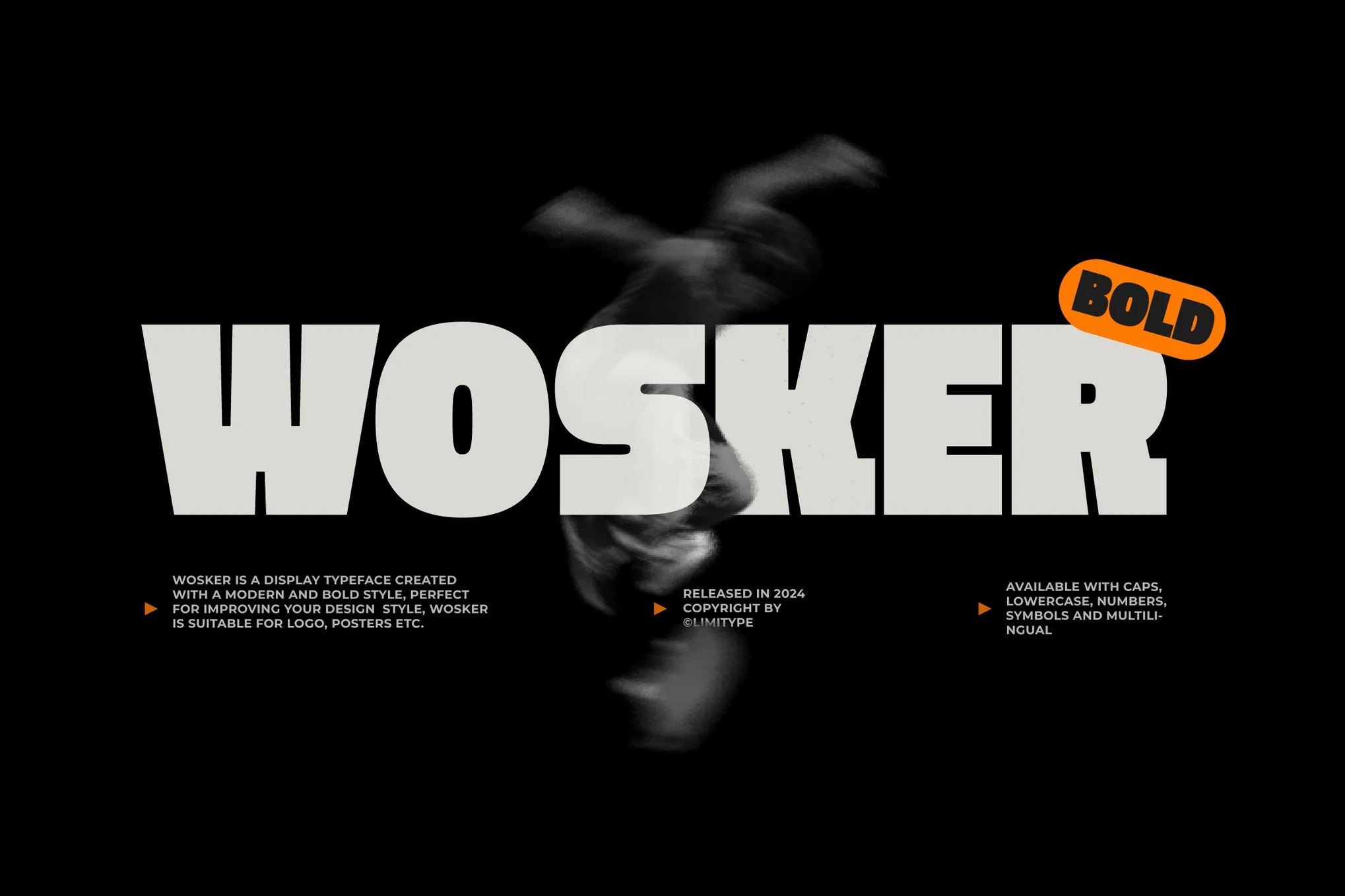
دانلود فونت Wosker – Bold Font
Wosker یک فونت نمایشگر با ویژگی های برجسته و مدرن است که برای طرح های شما مناسب است که به طراحی قوی، محکم و واضح نیاز دارند اما همچنان مدرن، دوستانه و نه سفت به نظر می رسند. فونت Wosker آماده پشتیبانی از طرح های شگفت انگیز شماست.